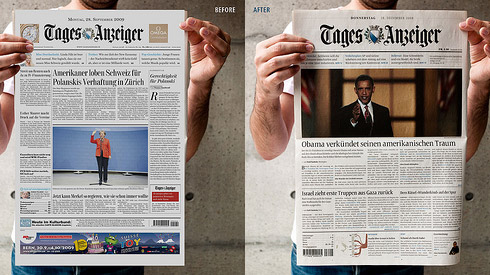
Zwei große Schweizer Tageszeitungen habe sich gerade einer Neugestaltung unterzogen. Zum einer die traditionelle Neue Zürcher Zeitung (wie diese es selbst bewertet; auch der Spiegel berichtete – wie gewohnt von oben herab – über das Redesign von Mike Meiré »Der alten Tante in den Nacken schlagen«). Eine Woche später folgte der ebenfalls in Zürich erscheinende Tages-Anzeiger, der von Tom Menzi und Daniel Stähli neu gestaltet wurde (die Beweggründe der Redaktion).
Mit im Rennen beim Pitch um die Tages-Anzeiger-Gestaltung waren die Information Architects (iA), eine Agentur mit Geschäftstellen in Zürich und Tokyo, die vorwiegend für ihre Internet-Projekte bekannt ist (und natürlich die Webtrend Map). Auf ihrer Webseite beschreiben sie in großer Ausführlichkeit, wie sie – als Außenseiter – alles auf eine Karte gesetzt haben und ein kompromissloses Konzept entwickelten, das scheiterte, aber nicht umsonst war. »We developed a pretty tight concept around the idea of usability, readability and cross media connection. The concept was: Use all knowledge from contemporary user experience design and translate it to paper. «
Bei der Präsentation ertappten sie sich dabei, wie sie statt »Titelseite« »Homepage« sagten und statt »Leser« »User«. Doch Fachleute, wie der große Mario García, lobten die Arbeit von iA. In seinem Blog schrieb er: »… there is SO MUCH to admire in the work of IA, such glorious use of creativity mixed with innocence that makes their project shine. Indeed, Oliver, there is a place for this model. There will be some courageous editor out there who will take it and run with it.«.
Im Beitrag von Oliver Reichenstein fällt mehrfach das Wort Leidenschaft. Manchmal reicht sie alleine nicht aus, um einen Job überzeugend zu meistern und zu präsentieren. Was gehört noch dazu? Der Pitch beim Tages-Anzeiger hat iA weiser gemacht. Sie gehen aufrecht aus dem Wettbewerb hervor und bewundern das realisierte Endergebnis. Wir können von ihnen lernen. Und daher habe ich iA heute zur TYPO 2010 eingeladen, die unter dem Motto Passion stehen wird.
der spiegel-artikel ist wirklich etwas bedenklich um nicht zu sagen völlig respektlos vor der wirklich hervorragenden arbeit von MM. so etwas »blind betrachtetes« sollte eher nicht aus einer kulturredaktion kommen.
Sehr schön, auch wenn man nicht alle Ideen, wie man im Web Informationen aufbereitet auf eine Zeitung übertragen kann und sollte. Der blaue Text würde mich enorm nerven, das Web-2.0-Logo ist zu zeitgeistig für eine altehrwürdige Zeitung, die Grafiken sind schön, aber vielleicht auch einen Touch zu hip fürs Blatt. Bei der Obama-Headline wird mir etwas schwindelig, zu breit, und generell ist die Typo zu groß, als Leser würde ich das nicht wollen. Generell sind online und Print verschiedene Medien und Print darf – zumindest noch und zurecht – eine tiefere Konzentration und weniger «Scannen» erwarten als ein Blog oder eine Newssite. Ein Zeitungsdesign, das die Sprunghaftigkeit von Online-Lesern berücksichtigt, versteht insofern vielleicht Zeitungsleser nicht.
Aber der Haupt-Kick-out-Grund: KEINE ANZEIGEN. Als Kunde würde ich jedes Zeitungs-Design, dass keine Anzeigen einplant, ablehnen. Damit verdiene ich nämlich mein Geld und Anzeigen sollten stets möglichst harmonisch in das Blattkonzept eingebettet sein.
Dennoch: Mutiges Konzept, großzügig umgesetzt, gut argumentiert und insgesamt schlüssig – vielleicht nur für die falsche Zeitung. Aber ich köööönnte mir vorstellen, das bei den beiden demnächst hoffentlich das Telefon klingelt und ein anderes Blatt Lust auf diese Art von Aufmachung hat.
Ich finde den Spiegel-Tonus gerechtfertigt. Ich mag Meirés Arbeit sehr oft, hier bleibt es im Kompromiss stecken. Entweder die NZZ richtig aufmischen oder aber größtenteils so lassen wie sie ist – nicht jede Zeitung muss krampfhaft modern werden und vor allem nicht diese Tante. Nicht jede alte Tante sieht im engen H&M-Fummel gut aus. Der Trend zum Weißraum in der Zeitung ist ja graphisch vielleicht schön, journalistisch aber eben scheiße. Autoren sollten nicht kürzer schreiben müssen, nur damit eine Zeitung (die kein Magazin ist) «luftiger» wirkt.
Und die NZZ ist, wie hier die FAZ, eben auch ein Sonderfall. Konservativ darf auch konservativ aussehen, finde ich.
Insgesamt etwas bedenklich, wenn die Zeitungen in einer Branchenkrise vergessen, was sie im Kern sind und sich nicht auf ihre Stärken besinnen….
Ich finde diesen Trend zu den sehr breiten Bildern sehr ärgerlich. Die Fotos dienen nur noch als bunte Fläche, Informationsgehalt gleich Null. Und wie man bei dem auch erst frischen Re-Design der Stuttgarter Zeitung sehen kann, wird dann sogar noch ziemlicher Bockmist gebaut, um ein Foto zwanghaft auf diese Un-Proportion hinzuzwingen.
Journalistische Fotos gibt es in den Zeitungen ja schon lang nicht mehr. Bunte, inhaltslose Flächen brauch ich nicht. Als Gestaltungselement in einer Sonntagszeitung, ok. Aber in einer Tageszeitung kann ich gut und gerne auf jegliche Fotos verzichten, wenn sie nur noch dazu dienen, die Seite mit Farbe aufzuhübschen. Farbakzente in der Typographie finde ich da wesentlich besser, weil man hier mit Farbe Struktur erzeugen kann.
Die Zeitungen rennen in die falsche Richtung, um junge Leser zu gewinnen. Wenn alles gleich bunt ausschaut und immer weniger Text, wo ist dann der Unterschied zur Online-Version der Zeitung? Dann lasst die Bäume stehen und spart euch das Drucken von Zeitungen gleich ganz.
Das Bohei um das IA Design finde ich völlig überzogen. Das ist ne saubere aber auch recht unspektakuläre, vorhersehbare Arbeit. Nicht mehr und nicht weniger. Und das trifft auf ziemlich alle Arbeiten zu, die ich von IA kenne.
Ich persönlich mag das klare ruhige Design. Die BILD-Zeitung tut mir selbst beim Bäcker auf dem Tresen in den Augen weh… Es gibt einen polnischen Grafiker der geniale Redesigns von Tageszeitungen gemacht hat. Ich suche den Link mal raus…